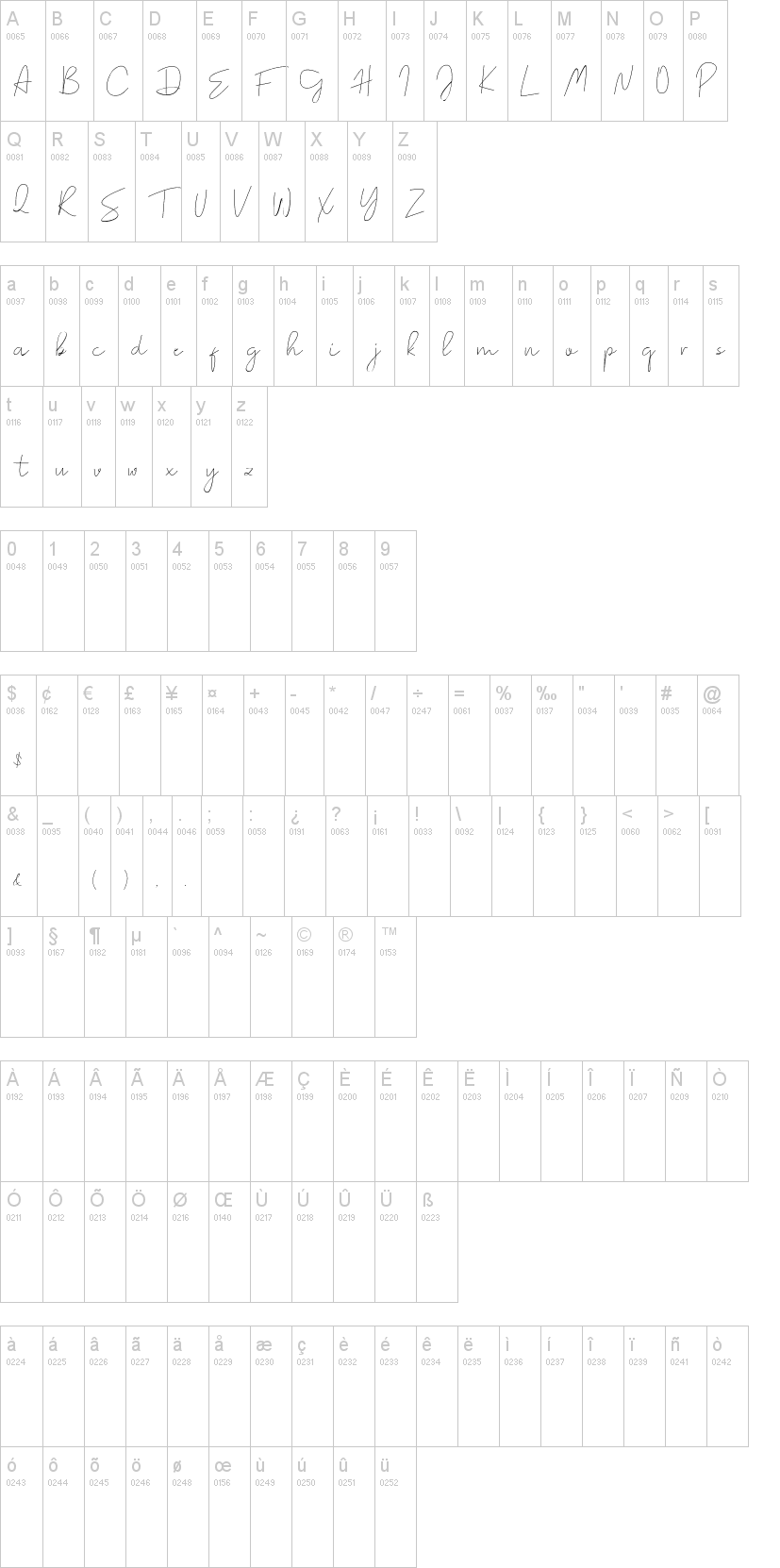
Romance Script
Romance Script 字体是一款花体字体,它由美国设计师 Richard Lipton 创作,是一款古典的花体字体,给人以温柔、浪漫的感觉。它的字体形状精致,线条柔和,细节处处洋溢着浪漫的气息,适合用于浪漫的场景,比如约会、婚礼等。Romance Script 字体拥有完整的英文字母、数字以及常用符号,可以满足各种使用场景的需求。
Romance Script是一款非常不错的手写艺术字体,具有很好的视觉感,适合于文化类的宣传设计、商业类品牌的广告和产品包装设计以及个性化文字排版等较多场景。
Romance Script字符映射图